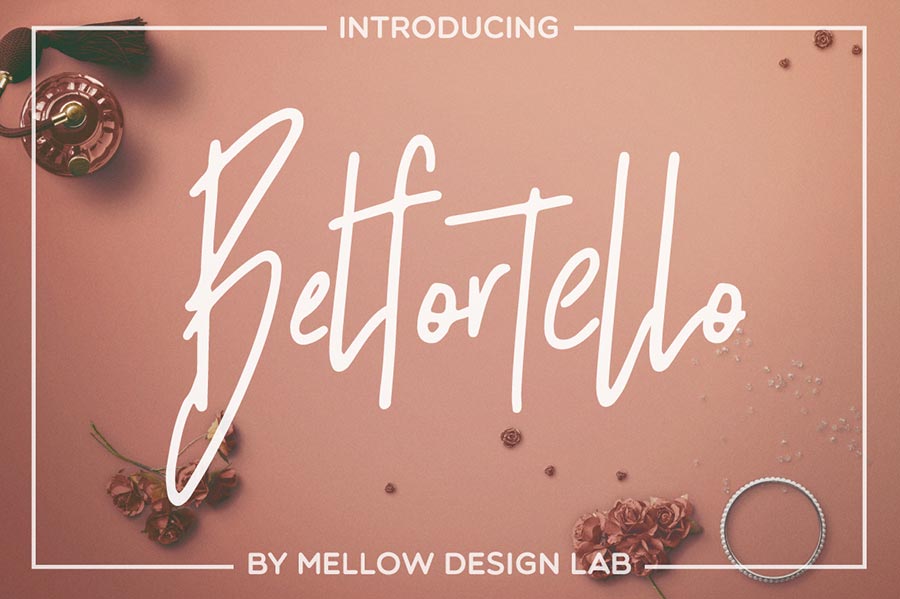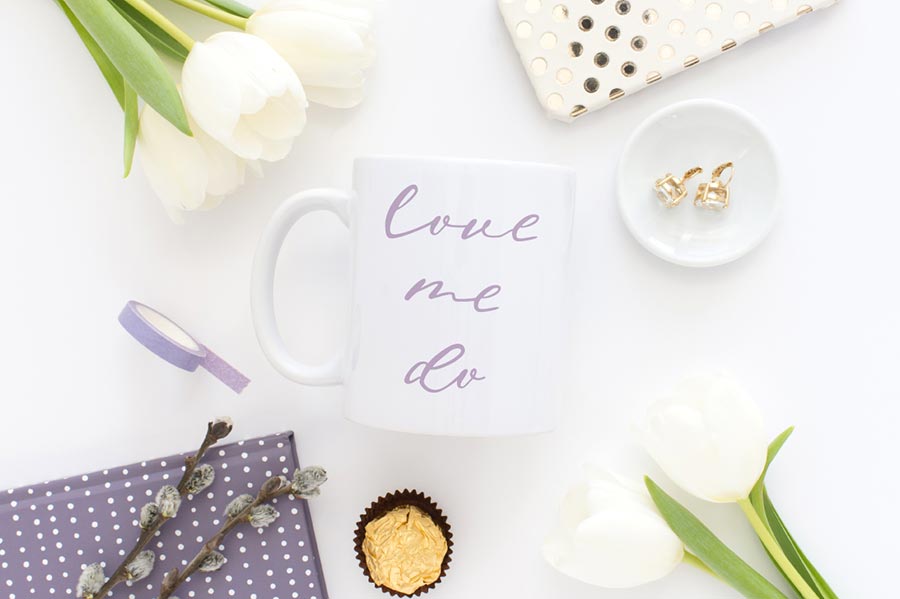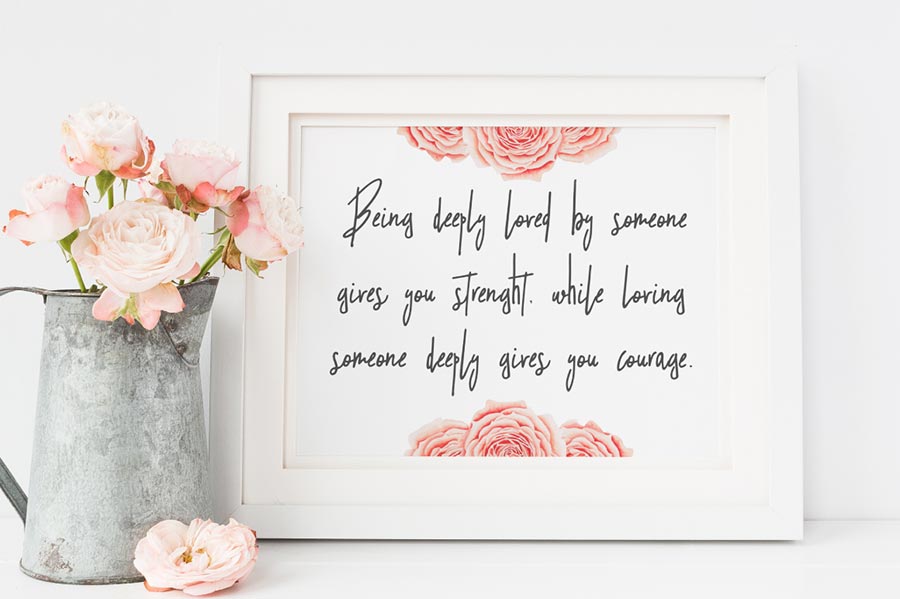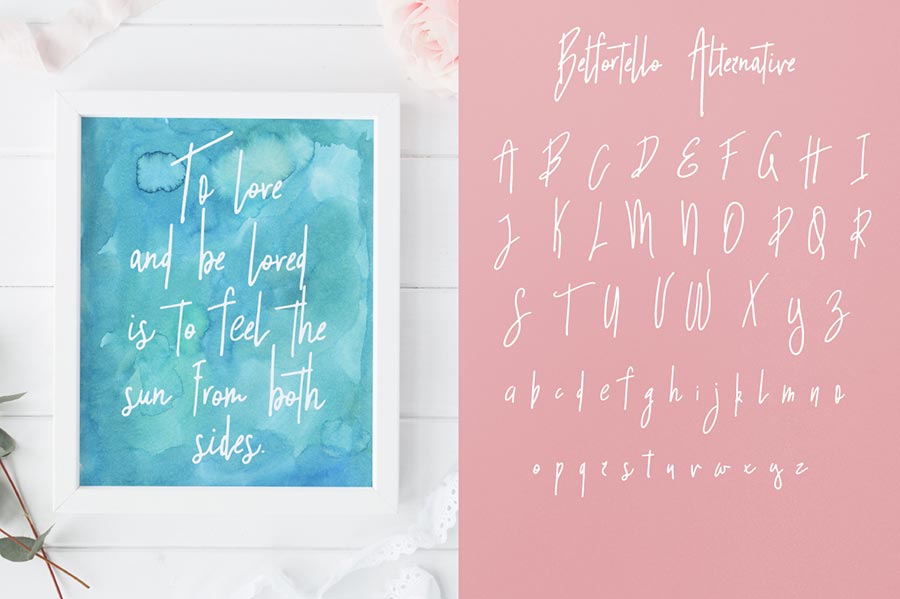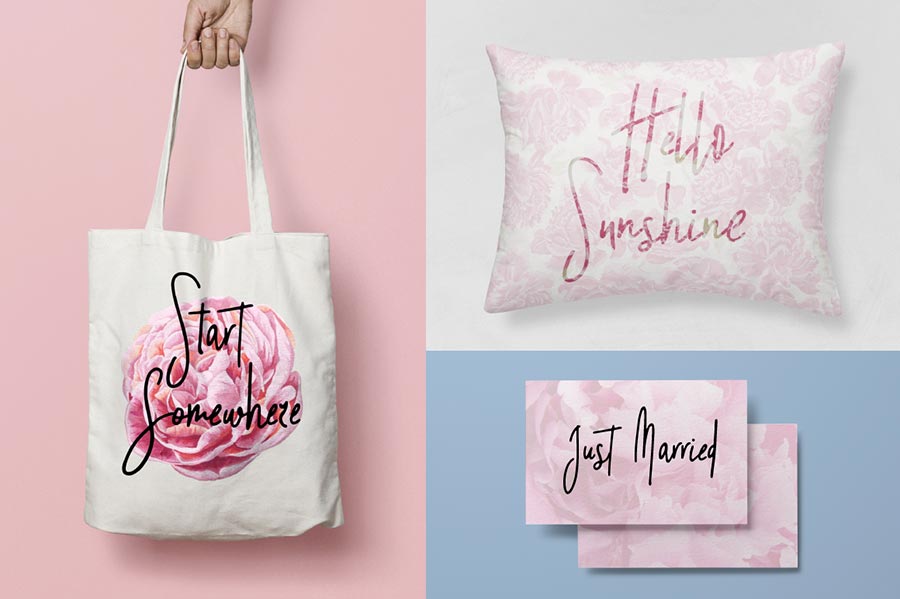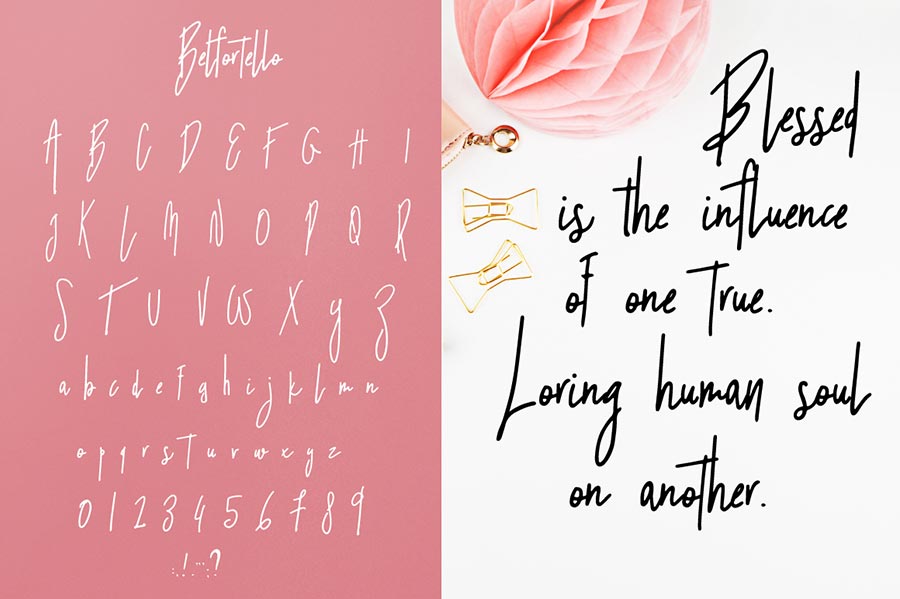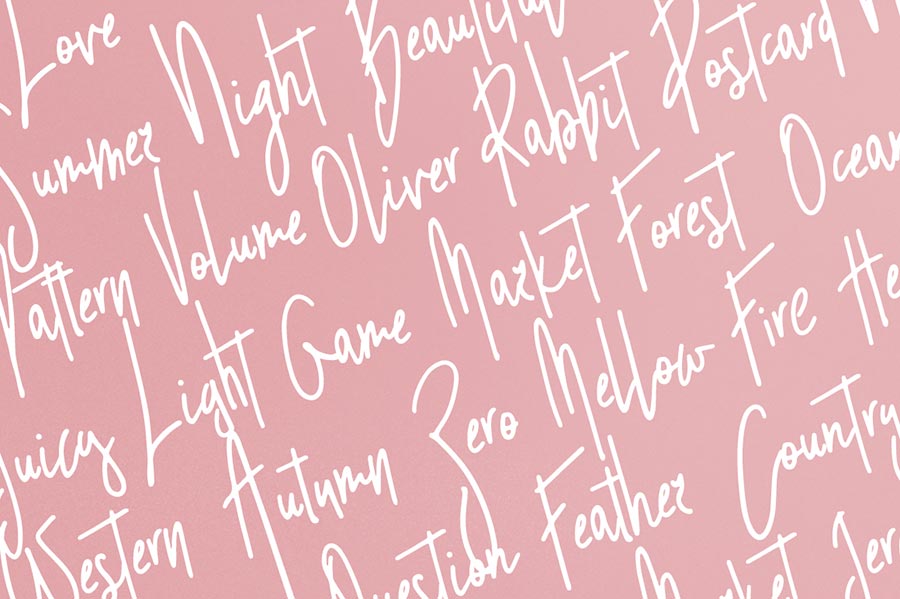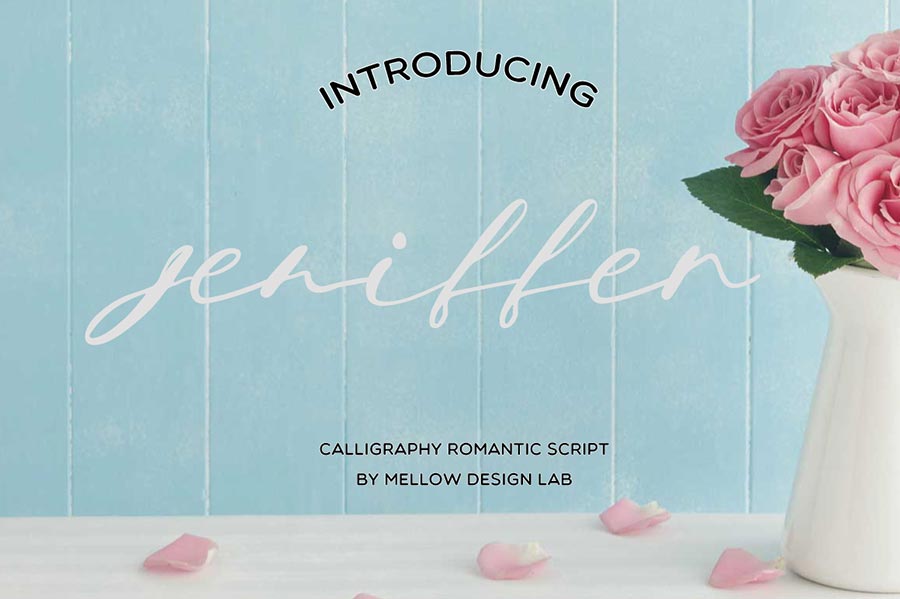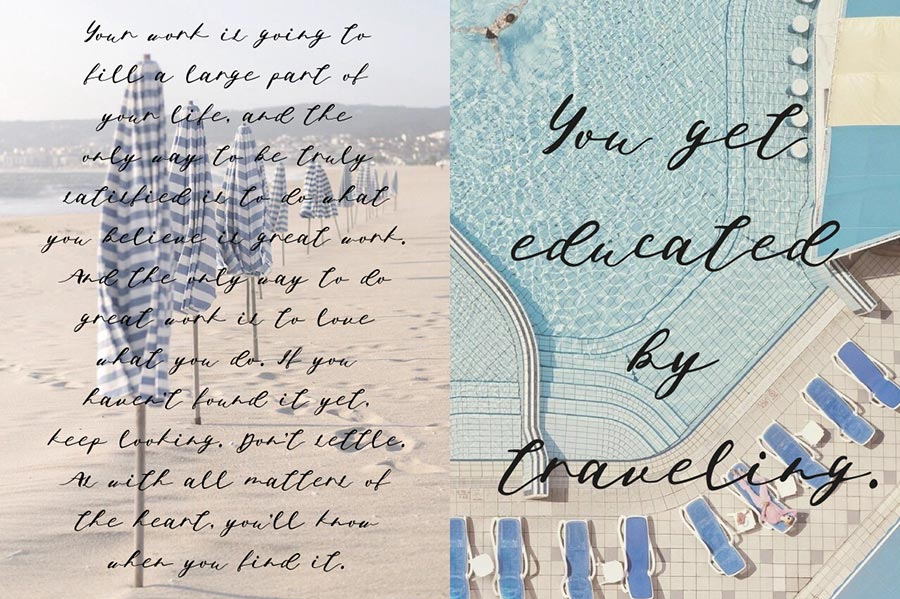
Chia Sẻ Miễn Phí 90+ Font Chữ Cực Xịn Xò, Chất Lượng
Với việc thiết kế đồ họa ngày càng trở nên quan trọng trong mọi lĩnh vực, việc lựa chọn đúng font chữ là một yếu tố then chốt để tạo nên sự khác biệt và thu hút người xem. Nếu bạn đang tìm kiếm những font chữ độc đáo, chất lượng cao và đặc biệt là miễn phí, sadesign.vn là nơi bạn không thể bỏ qua. Họ cung cấp hơn 90 font chữ chất lượng, đa dạng về phong cách, hoàn toàn miễn phí cho bạn tải về và sử dụng. Cùng khám phá bộ sưu tập tuyệt vời này để nâng tầm thiết kế của bạn!
Bộ Sưu Tập Font Chữ Miễn Phí Từ Sadesign.vn
Font Chữ Đơn Giản, Thanh Lịch
Bộ sưu tập font chữ của sadesign.vn không chỉ có những font chữ phức tạp mà còn có nhiều lựa chọn đơn giản và thanh lịch. Những font này rất phù hợp cho các dự án cần sự tinh tế, nhẹ nhàng như thiết kế logo, thiệp cưới hay các quảng cáo trang nhã.
Font Chữ Nghệ Thuật, Cá Tính
Nếu bạn đang tìm kiếm những font chữ mang đậm phong cách nghệ thuật và cá tính, sadesign.vn cũng có đầy đủ lựa chọn. Những font này thích hợp cho các thiết kế poster, banner hoặc các sản phẩm sáng tạo, giúp tăng tính độc đáo cho tác phẩm của bạn.
Font Chữ Cổ Điển, Sang Trọng
Không thể thiếu trong bộ sưu tập là những font chữ mang phong cách cổ điển và sang trọng. Những font này đặc biệt lý tưởng cho các dự án yêu cầu sự sang trọng, thanh thoát, chẳng hạn như thiết kế bao bì sản phẩm, sách hoặc các ấn phẩm in ấn cao cấp.
Font Chữ Hiện Đại, Đột Phá
Bên cạnh những phong cách cổ điển và nghệ thuật, sadesign.vn cũng cung cấp các font chữ hiện đại, đột phá. Những font này có thể làm nổi bật các thiết kế sáng tạo, đầy tính ứng dụng trong các lĩnh vực công nghệ, startup hoặc các sản phẩm quảng bá thương hiệu.